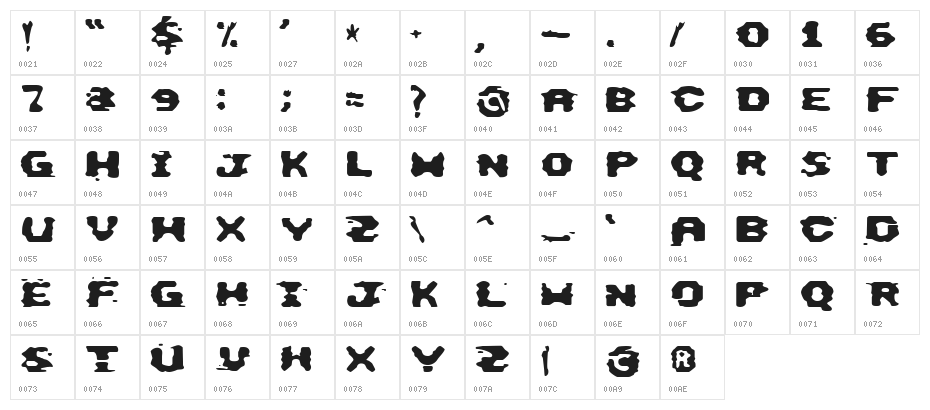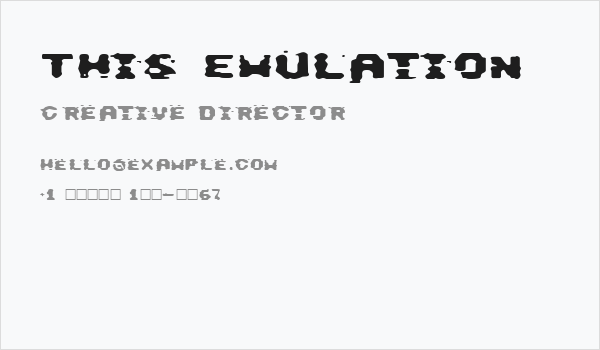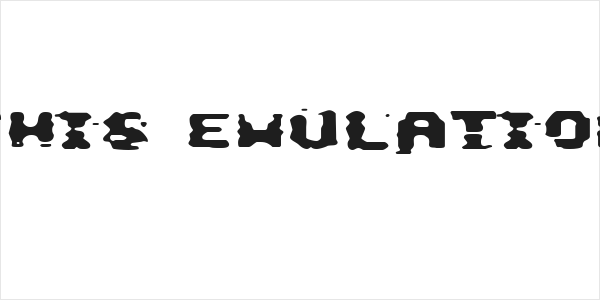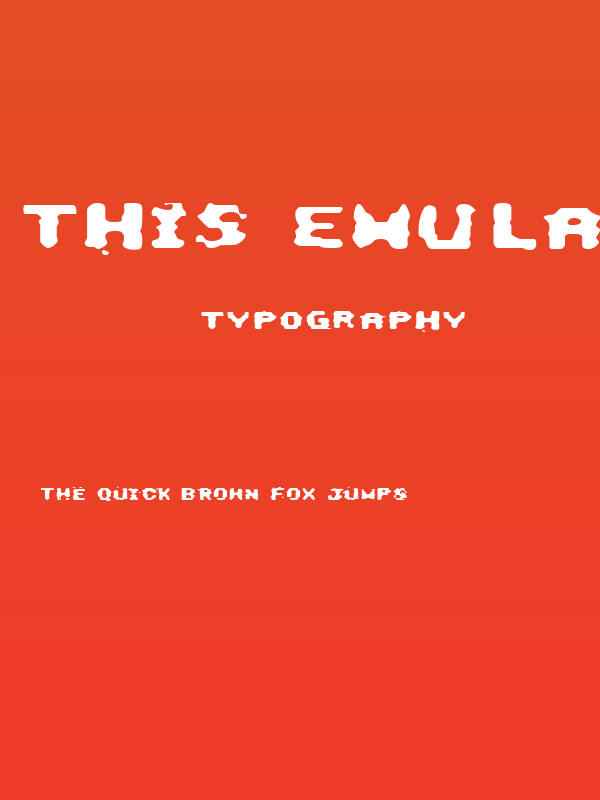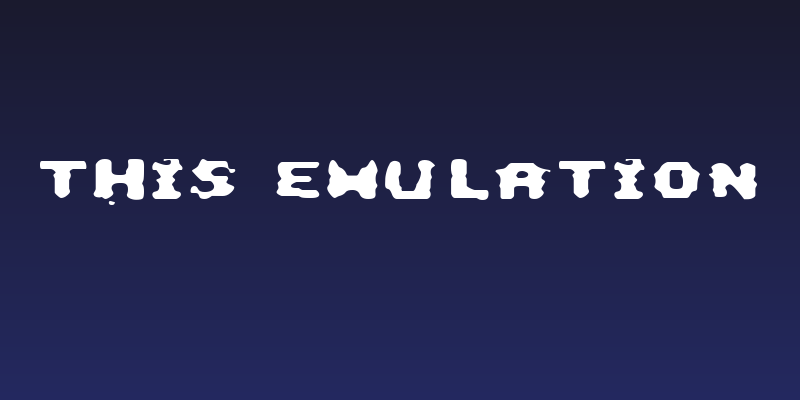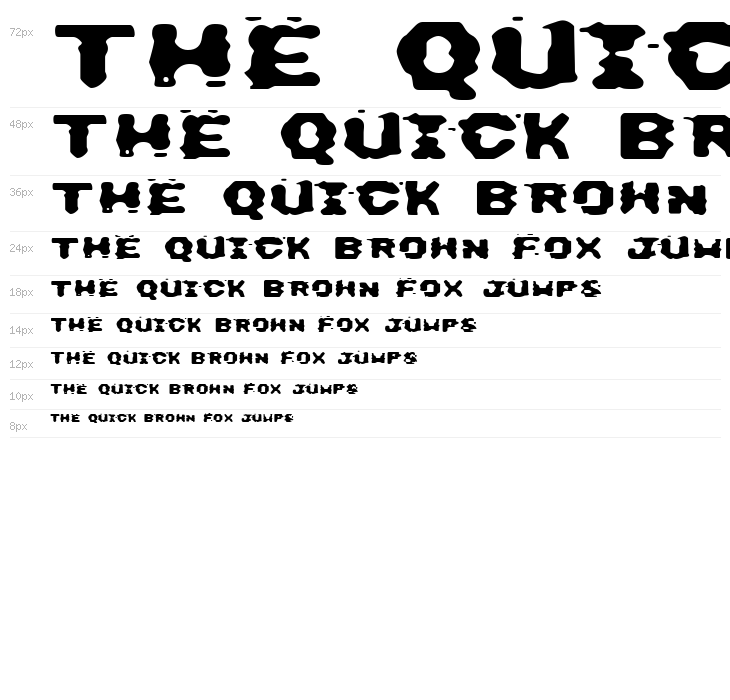
This Emulation Font
| Kategorien | Decorative |
| Gesamtstil | Grunge, Industrial |
| Vorgeschlagene Projekte | Ideal for album covers, posters, urban-themed designs, and branding that requires a gritty aesthetic. |